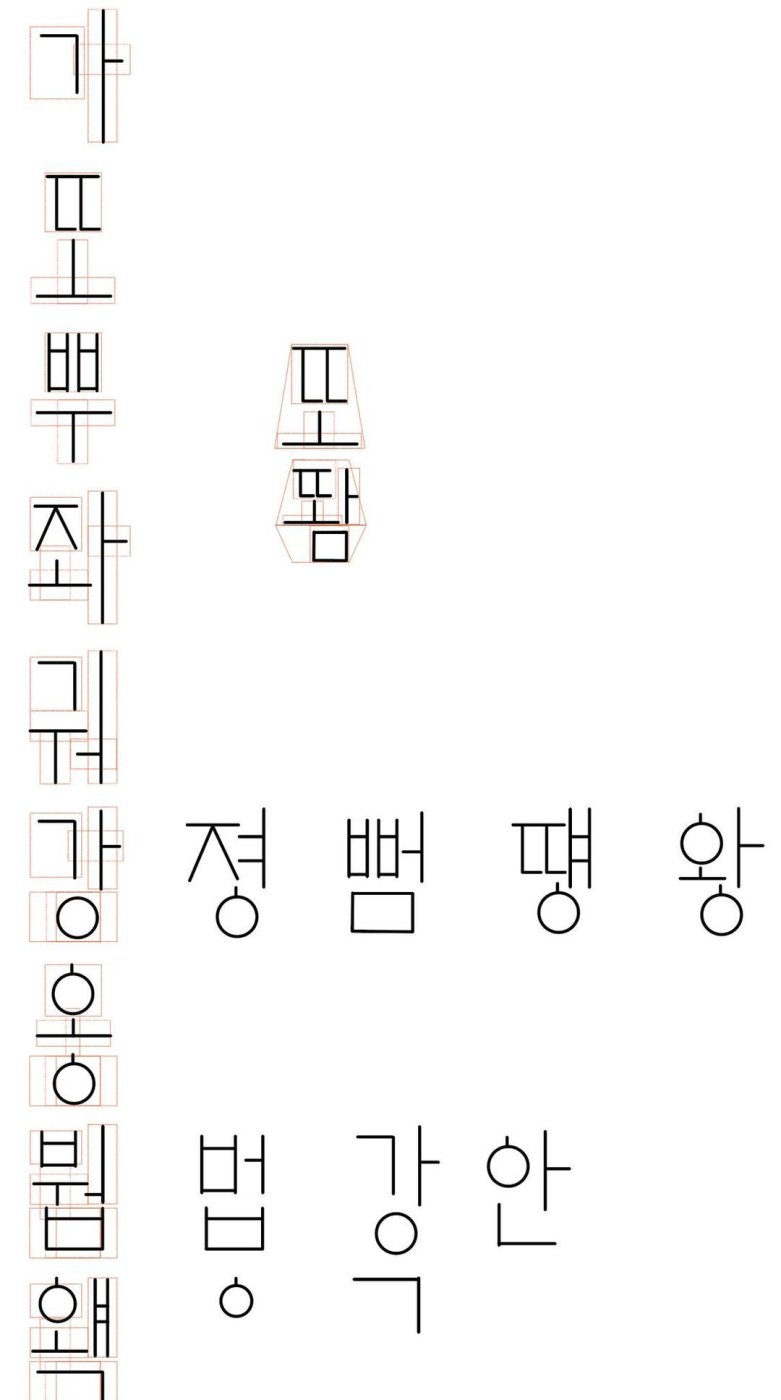
나만의 한글 폰트 제작을 더 쉽게
폰트제작 시간을 줄여주는 방법론
폰트 그리드를 먼저 에디터로 만들면 거기에 맞춰 자신의 손글씨 스타일을 직접 적용하는 방식으로 바꿈... 초성, 중성, 종성 몇벌이 들어가는지는 결국 어떤 폰트 형태로 만들지에 따라 ㅔㅖㅓㅣㅏㅒㅑ에 붙는 초성만 몇벌이 들어감 일율적으로 너비만 맞추면 한글이 이상해짐
인공지능이 만드는 글자들이 대부분 비슷한 이유가 학습하는 스타일이 몇가지 레이아웃을 기준으로 진행되기 때문에 반대로 내 글씨와 비슷한 폰트 유형의 그리드를 만들고 120개, 250개, 500개 초, 중, 종 조합의 폰트가 만들어지게 되며 확장을 위해 더 많이 넣을 수록 상업용에 가까운 폰트로 제작이 가능합니다. 그래서 온라인에 엄마의 손글씨를 넣으면 몇가지 템플릿에 글자를 쓸 수 있는 가이드가 실시간으로 제작되어 PDF를 받게됩니다.
인쇄해서 보낼 수도 아이패드 앱에서 글씨쓰면 끝나는 방식이고 수정해서 글자조합이 된 PDF를 먼저 웹에서 확인
TTF, OTF 파일과 파일 구조에 맞춰 폰트가이드와 조합했을 때 잘못된 것을 모두 확인해주는 리포트를 제공합니다. 폰트 에러는 의외로 많이 발생합니다.
디자이너면 2단계 정도면 자신의 폰트를 만들 수 있음 폰트조합만 3일 걸린다고 하니까 그걸 1분 정도 만에 끝내서 제공
이제 폰트는 그냥 취미...
석보상절 폰트 가이드 실제 폰트에디터 글리프나 폰트포지에서 사용하는 방식이 아니며 일러스트레이터에서 폰트 만드는 용도로 제작한 가이드입니다. 현재 웹에서 가이드를 편집하는 기능 작업을 하고 있습니다.
엄마/아빠 글씨로 폰트를 만들어 가족의 기록을 모아 책으로 만들어 드리는 기획은 여전히 하고 있습니다.